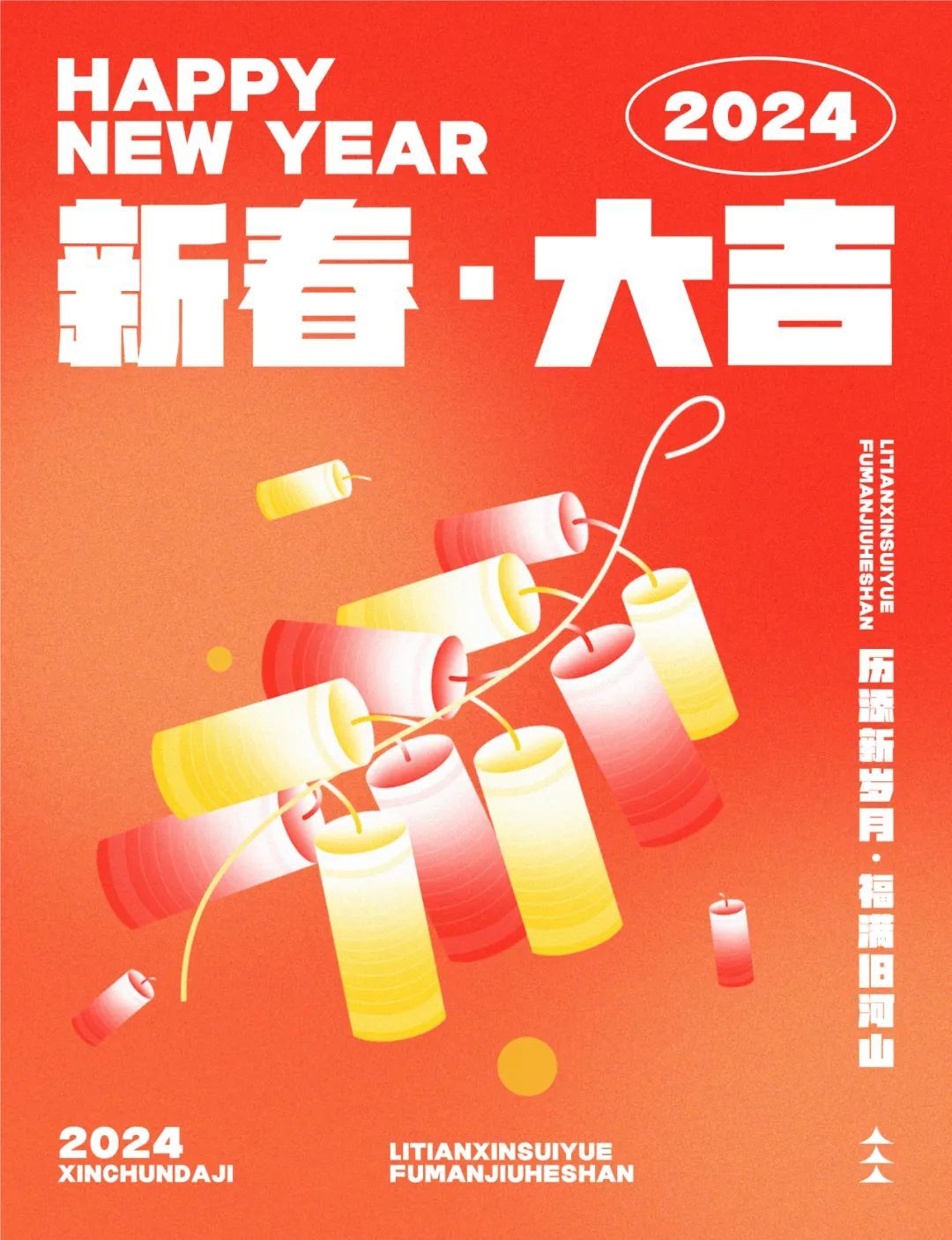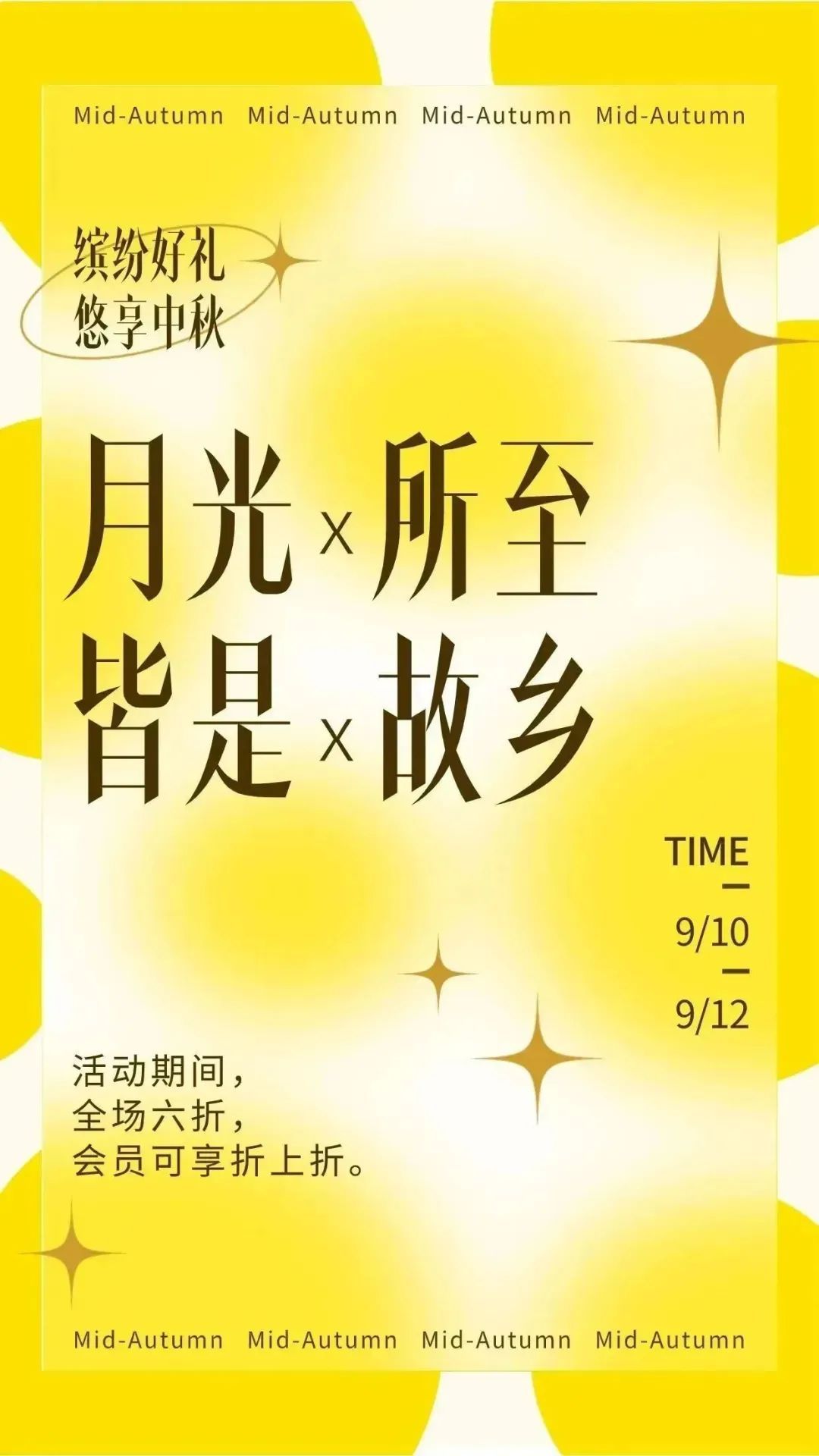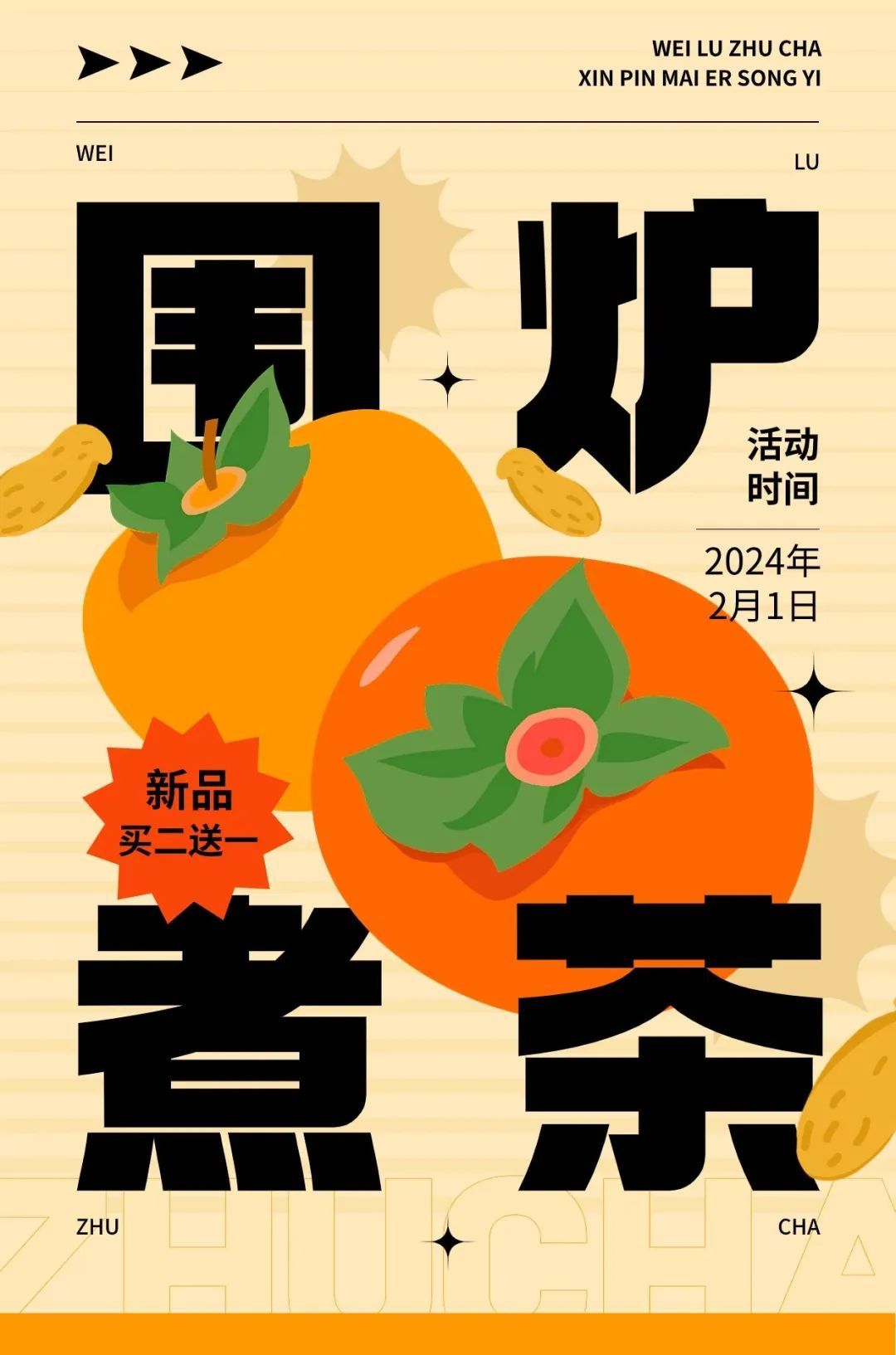
高手字造 | 刘兵克字库入驻励字造梦共创字库,开启造字艺术新境界!
刘兵克字库,于2023年正式发布,首发15套中文字库,创始人为字体设计师刘兵克,其字形风格各有特色,能满足设计师群体在各个行业、各种场景的字体使用。
刘兵克字库加入造字侠联盟高手字造计划,现已入驻励字造梦共创字库,上线高手兵克系列字体15款,共同开启字库合作新篇章,现在双方将各自在字体设计与技术创新领域发挥优势,深度合作,共筑字库新生态,探索更多可能性和合作模式。
-高手兵克高雅宋-
高手兵克高雅宋,是一款偏瘦长的宋体字,中宫偏大,重心平稳居中,字体结构均匀,字形呈瘦高状,挺拔而俊俏,瘦高的字形体现出优雅的韵味,既有宋体的高雅书卷气质,又不失力量感。尤其在竖笔画处的斜切处理,呈现一种极冷静、极克制、极简洁的文字高雅之美。
-高手兵克泰山体-
高手兵克泰山体,是一款兼具稳重力量感和几何形态的创意黑体,风格醒目、充满张力。字面大而中宫放松,字形视觉整体轮廓为正梯形,为字体增加了沉稳感。笔画特点横细竖粗、疏密分布合理且横笔画起收笔处融入斜切处理,呈倒梯形,使得该字体结构醒目有力的同时更具有强烈的视觉表现力。
-高手兵克雷霆体-
高手兵克雷霆体,是一款创意黑体字。整体字形内部结构平稳舒畅、布白均匀使字体拥有简洁干练、坚韧牢固的特点。笔画设计简洁而不呆板,部分笔画方直形态与圆弧形态结合,在保持结构稳定的前提下丰富了字体个性,给人以强烈的视觉冲击感,多了些装饰意味。
-高手兵克坚黑体-
高手兵克坚黑体,笔画厚重有力,字形敦厚,笔势连贯有序,整体字形给人以醒目、坚实之感,极具现代感。
-高手兵克柔黑体-
高手兵克柔黑体笔画柔中带刚,字形端正,笔画横平竖直,简洁大方,字形结构严谨,实用性强。